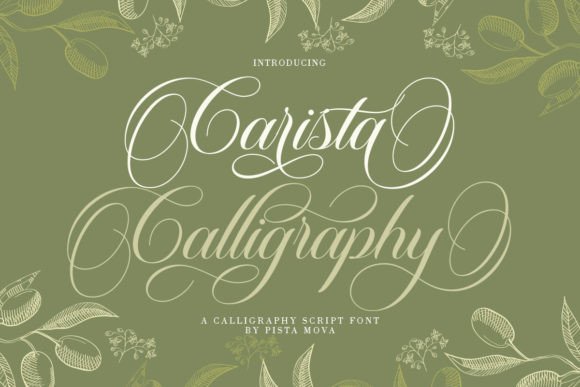
Carista Calligraphy
Carista Calligraphy – La police élégante qui sublime vos créations
Vous cherchez une typographie à la fois classique et moderne pour sublimer vos projets ? Carista Calligraphy répond parfaitement à ces exigences. Grâce à ses courbes raffinées et à ses riches fonctionnalités OpenType, elle s’impose comme le choix idéal pour les supports où le style formel ou sophistiqué est de mise.
Pourquoi choisir Carista Calligraphy ?
- Polyvalence exceptionnelle : convient aux invitations de mariage, couvertures de livres, cartes de vœux, logos, branding, cartes de visite et certificats.
- Élément moderne intégré à un design traditionnel, offrant un rendu à la fois intemporel et actuel.
- Fonctionnalités OpenType avancées (ligatures, alternates, petites capitales) pour un contrôle total du rendu typographique.
- Impact émotionnel : son charme élégant apporte joie et créativité à chaque projet.
Idées d’application concrètes
- Cartes d’invitation de mariage – donnez une touche romantique et sophistiquée.
- Couvertures de livres – créez un titre qui attire l’œil et reflète le ton du récit.
- Logos de marques de luxe – renforcez l’image premium avec une calligraphie raffinée.
- Cartes de vœux personnalisées – transmettez vos sentiments avec style.
- Certificats et diplômes – ajoutez une note d’autorité et de prestige.
Boostez votre créativité avec Carista Calligraphy
En intégrant Carista Calligraphy à votre boîte à outils, vous bénéficiez d’une police qui allie tradition et modernité, tout en restant simple d’utilisation. Laissez son élégance inspirer vos projets, augmentez votre productivité et offrez à vos clients une expérience visuelle mémorable.